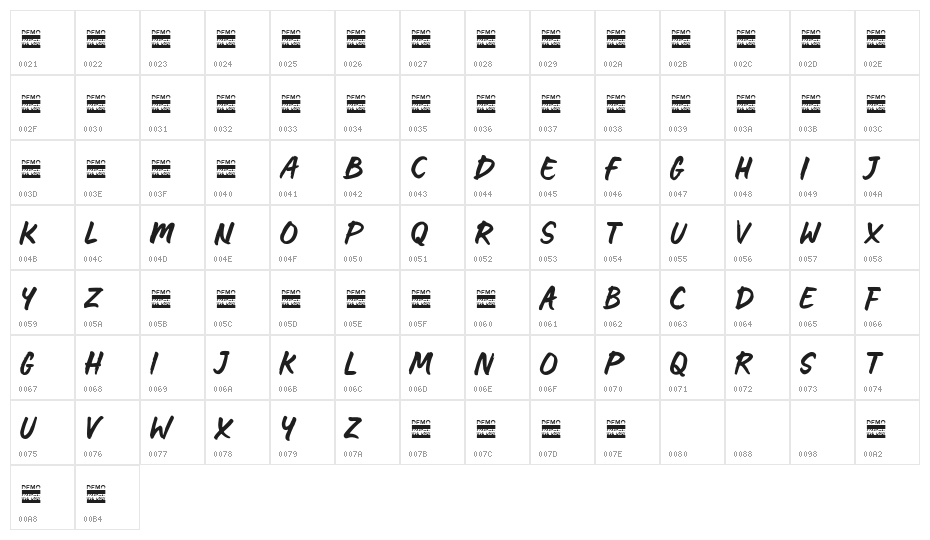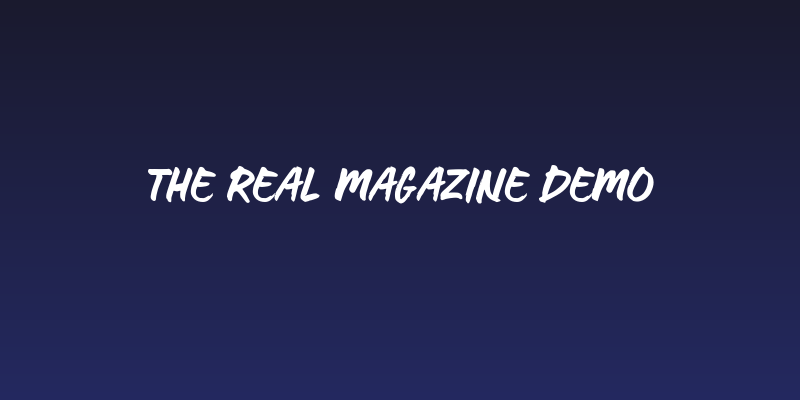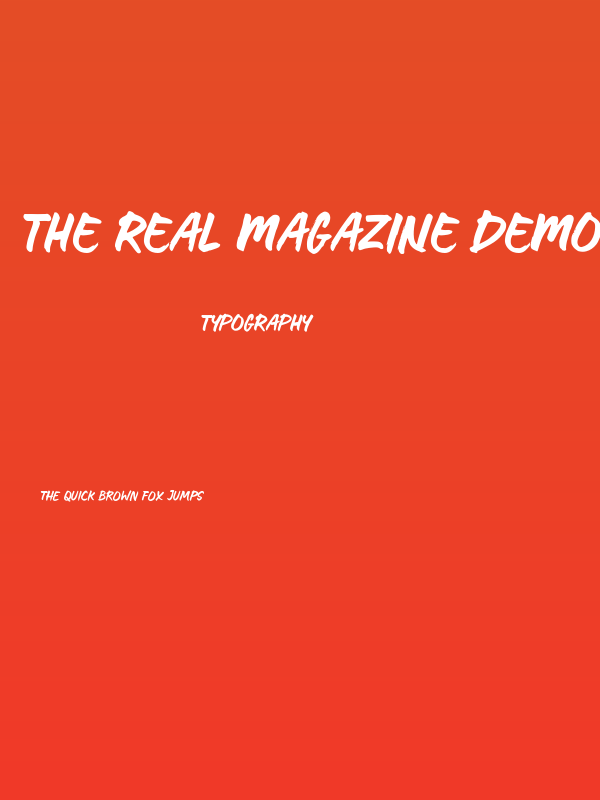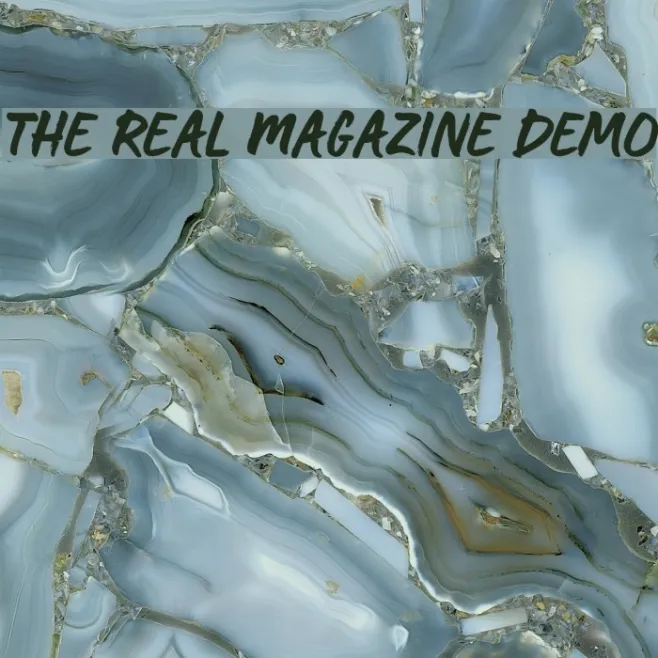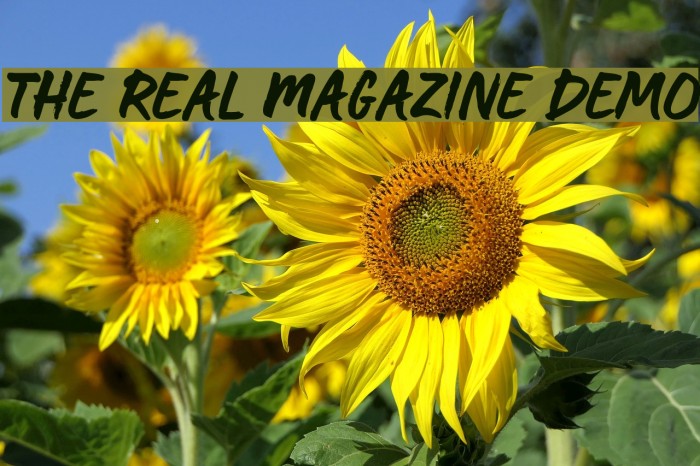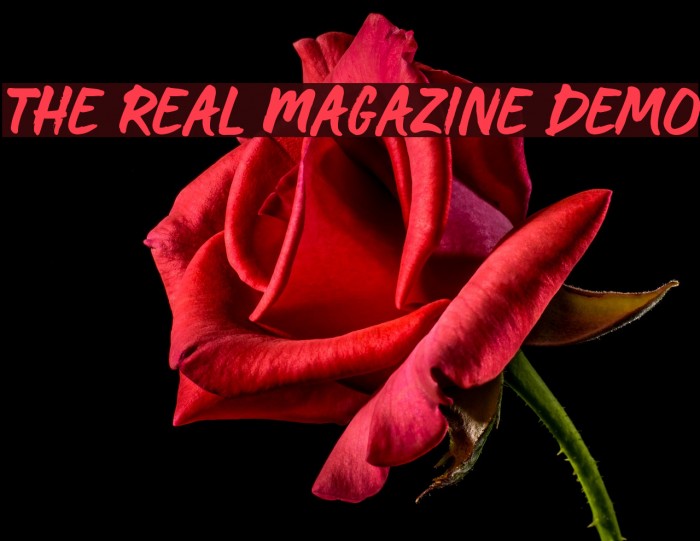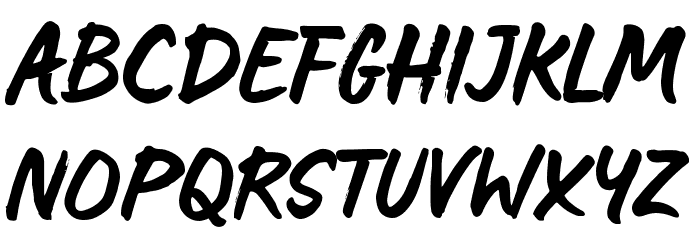
The Real Magazine Demo Font
✎ Script
| Kategorien | Script |
| Anwendungsfall | Logos, Headlines, Posters |
| Vorgeschlagene Projekte | Ideal for branding, posters, social media graphics, and any project needing a dynamic, artistic touch. |